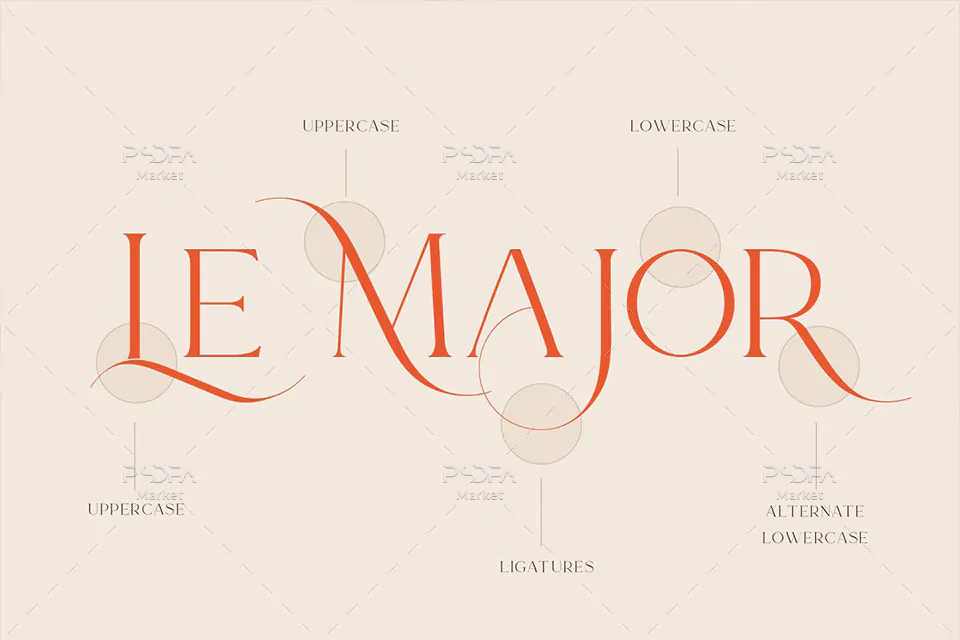
فونت انگلیسی نمایشی سریف Le Major مناسب برای طراحی لوگو
فونت انگلیسی نمایشی سریف Le Major
فونت Le Major در وزن معمولی (Regular) طراحی شده است که میتوانید از آن در طراحی انواع کارت تبریک، کارت پستال، کارت ویزیت، کارت عروسی، کارت دعوت، طراحی لوگو، طراحی بسته بندی محصولات آرایشی و بهداشتی، کاور آلبوم موزیک، طراحی انواع بنر، پوستر، تراکت، تقویم و دیگر طرحهای گرافیکی استفاده کنید. از نسخه woff این قلم نیز میتوانید در طراحی صفحات وب استفاده کنید.